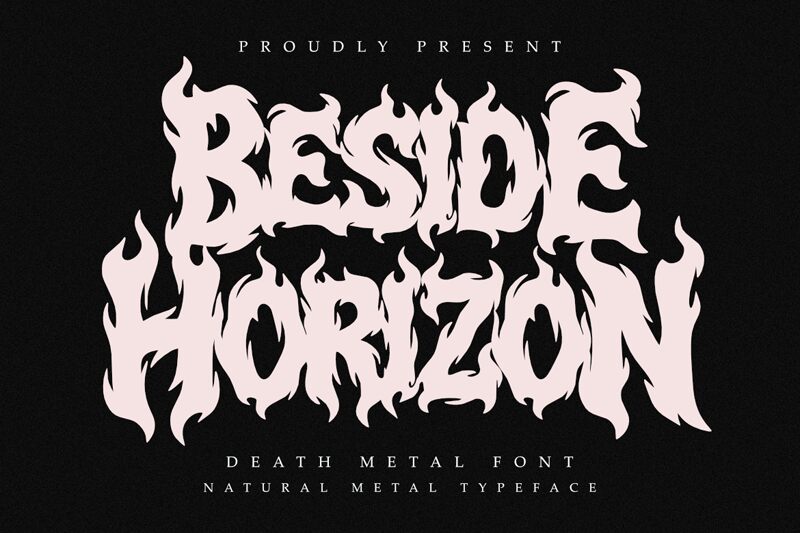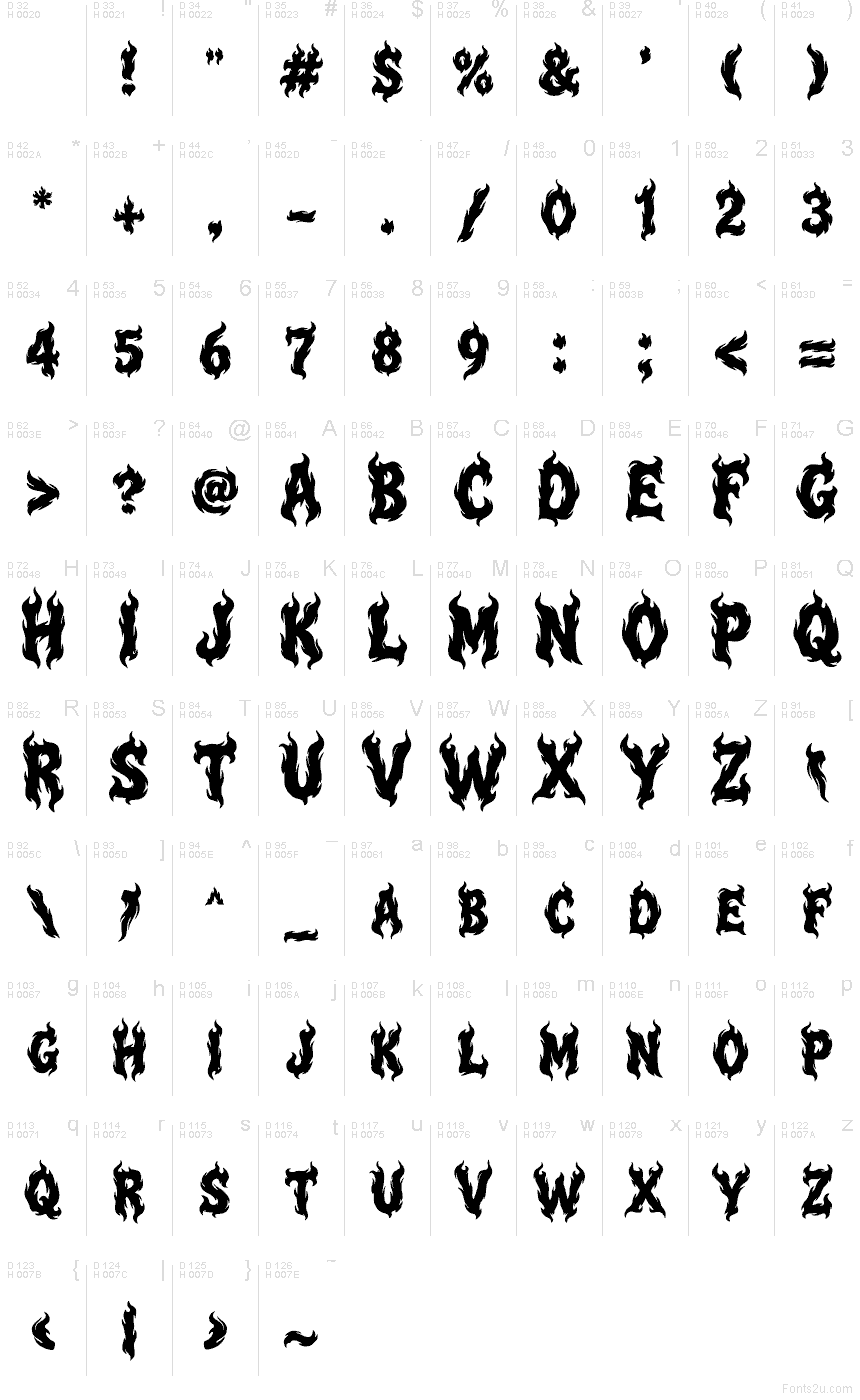
Beside Horizon, de Masyafi Studio, es una tipografía display de terror gratuita con letras que parecen lamidas por el fuego y desgarradas por el humo. Sus siluetas irregulares y trazos sinuosos le dan una atmósfera febril, como de título de película de miedo, mientras que sus formas pesadas mantienen la tipografía lo suficientemente audaz y legible como para ser una declaración gráfica en sí misma.
Encaja a la perfección en titulares de pósteres, portadas de álbumes, flyers de festivales, títulos de juegos y branding de Halloween donde el lettering necesita sentirse volátil en lugar de pulcro. Al ser una fuente gratuita, también funciona muy bien para eslóganes comerciales cortos o gráficos para redes sociales, ya que sus bordes quemados y dinámicos hacen gran parte del trabajo atmosférico por sí solos.